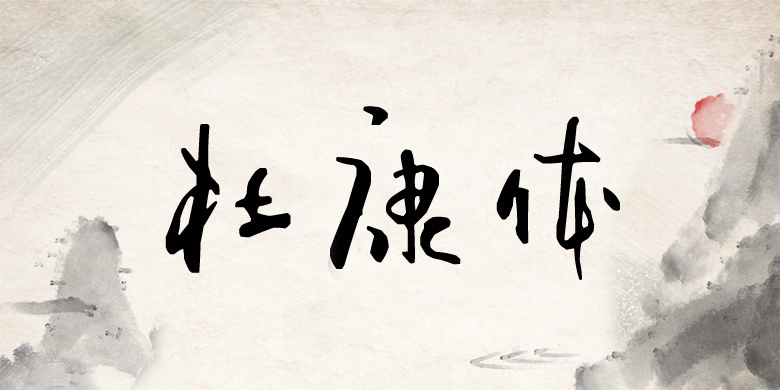
品牌:方正手迹设计师:马军长发行时间:2016字库编码:大陆简体(GB2312-80)分类:常规书写·毛笔字体属性:精品字
当你看到这个字的结字形态,你就会知道为什么它叫杜康体。出其不意的构字方式,富有创意的部件形态,使该字仿仿佛是酒后所作。而最值得品味的是其具有传统书法美的内核。适用于现代诗歌、短文的排版以及文化、商业类品牌的广告语设计。